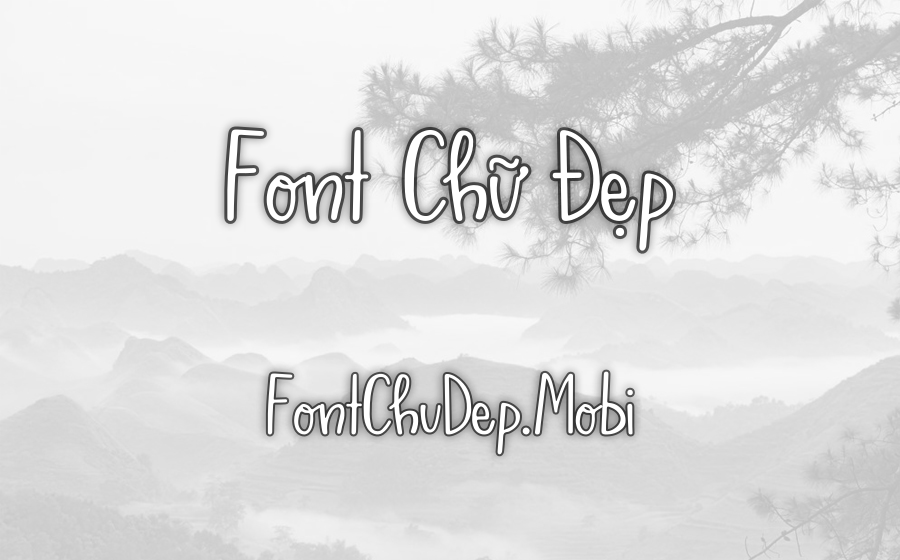
Font SVN Air Balloon Việt Hóa
SVN Air Balloon
Trong thế giới của những kiểu chữ độc đáo và sáng tạo, Air Balloon là một font chữ viết tay mà tôi không thể không chia sẻ cảm nhận đầy thú vị về nó. Được thiết kế bởi Misti’s Fonts, Air Balloon không chỉ đơn thuần là một font chữ thông thường mà còn mang trong mình vẻ đẹp thủ công đầy ấn tượng. Với nét chữ mềm mại và độ tương phản tinh tế, font này thực sự là lựa chọn lý tưởng cho nhiều dự án thiết kế từ thiệp mời, tiêu đề cho đến áo thun và các sản phẩm quảng cáo.
Điểm đáng chú ý của Air Balloon chính là sự dễ đọc ở mọi kích cỡ, nhờ cấu trúc chữ uyển chuyển và thân thiện. Điều này giúp font trở thành một công cụ đắc lực cho nhà thiết kế muốn tạo dấu ấn khác biệt trong các sản phẩm nghệ thuật và giáo dục, quảng cáo và sự kiện. Hơn nữa, với hơn 200 ký tự cùng hỗ trợ nhiều ngôn ngữ, bao gồm cả tiếng Việt, Air Balloon mở ra cơ hội sáng tạo không giới hạn cho người dùng trên toàn cầu.
Dù bạn là một nhà thiết kế chuyên nghiệp hay chỉ đơn thuần là người yêu thích làm mới bản thân qua các sản phẩm cá nhân, Air Balloon chắc chắn sẽ mang lại cảm giác vui nhộn và độc đáo cho mọi tác phẩm của bạn.